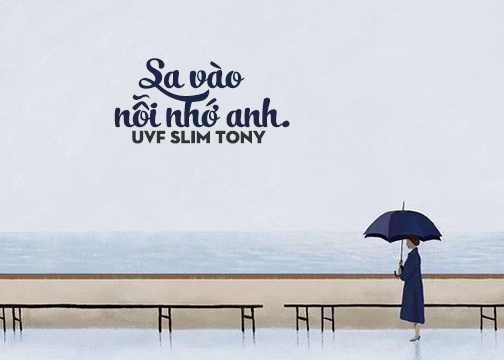
[Font] UVF Slim Tony
Share font nữa đây =))) mình muốn share mấy cái khác nữa nhưng mình chỉ thích font và chỉ mới học pts =))))) Font này đơn giản, dễ thương, phù hợp cho mấy bạn des/edit bìa lắm, mình nghĩ vậy. Ai cần và chưa có font này thì, vote chap này và comment gmail bên dưới nha.